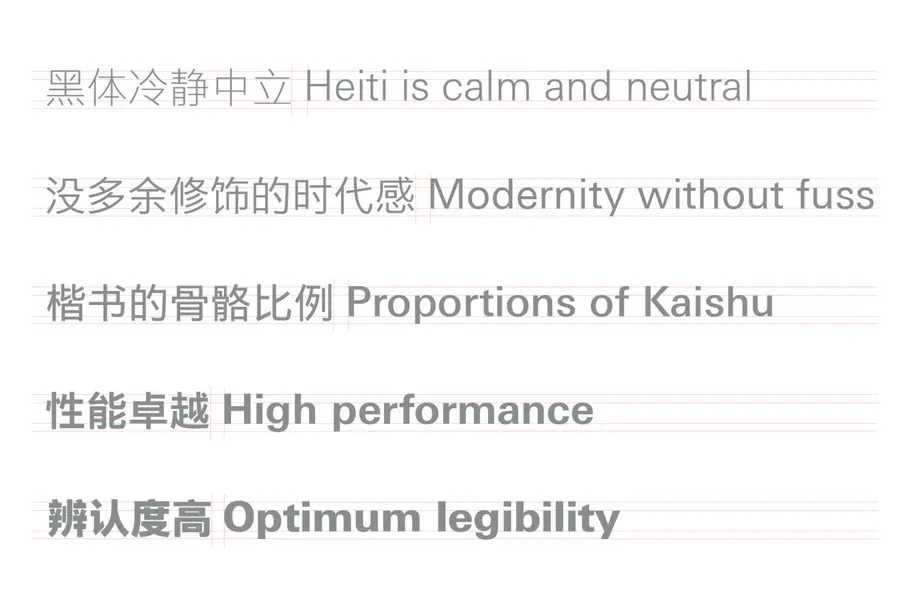
デジタル向けの中国語書体にサンセリフ体が誕生
M Ying Hei™は、Monotypeの熟練した書体デザイナーと長年コラボレーションを行ってきたKenneth Kwok、Robin Huiによってデザイン、制作されました。デジタルデバイスのインターフェイスと印刷媒体の両方で優れたパフォーマンスを発揮し、よりモダンでエレガントな中国語サンセリフ体を求める声に応える書体の開発に成功したのです。
ベストセラーの中国語書体を21世紀向けに一新
まず、M Ying Hei書体の由来をご紹介します。M Ying Heiは、優雅で上品な書体M Heiに大きなインスピレーションを受けています。M Heiは、1990年代にMonotypeがリリースしたクラシックなデザインの書体で、発表されるや否や瞬く間に中国語サンセリフ体のベストセラーとなりました。M Heiは、中国語繁体字の正式書体「楷書体」の構造とプロポーションをベースとしながら、ミニマルで鋭いストロークのデザインを取り入れたことから、Heiti系書体に分類されています。Heiti系は、1500年もの間、中国語における漢字の形体を定義してきた精巧な楷書体から装飾的要素を取り除いた、非常にシンプルな字体です。
M Ying Hei サンプル
中国語書体のすべてのカテゴリにおいて、Heitiはグラフィックデザイナーの間で最も人気のある書体となり、現代中国のライフスタイルを表現する代表的な文字としての存在を確立しました。それは、西洋でグロテスク・サンセリフ書体(Helvetica®など)が現代的な字体として定着したのと同じ現象と言えるでしょう。Heitiは、装飾要素を廃した落ち着いたトーンの書体で、読み手にモダンな雰囲気を印象づけます。言語の境界を越えて使用が可能で、縦横の線の太さが同じ書体ときれいに調和します。
Kaishuと同様の質を備えていることから、M Heiは他のHeitiデザインとは対照的に、比較的クラシックな構造をしています。
古いKaishu書体と新しいHeiti書体の両方の良い部分を併せもつM Heiは、中国語書体の世界における「稀に見る宝石」との呼び名が付くほどのデザインとなりました。また、香港と台湾では過去25年間にわたり、継続して読み続ける長文書用の書体として最も好まれる書体となりました。そして、モバイル技術の時代が到来したのです。
情報時代のための中国語サンセリフ体
携帯電話などの小型画面用に、滑らかで、可読性と柔軟性の高い中国語の書体に対する需要が高まることを予見したMonotypeの書体デザインチームは、デジタル画面でも美しく表示される高性能のHeiti書体の開発に乗り出しました。MonotypeのM Ying Hei書体は、この新しい時代の到来を念頭に制作されました。
M Ying Heiでは、漢字の中央部を広く取ることができます
かつては不可能だったことが、この新しいデザインで可能になったのはなぜでしょうか。M Ying Heiは、漢字の中央部を広く取ることができるのです。これは、ラテン文字でエックスハイトを大きくするのと似ています。この調整が可能になったことで、Neue Helveticaのようにはっきりとした機能的な書体との組み合わせが非常に美しく仕上がり、モダンで親しみやすい雰囲気を生み出すことができるようになりました。
また、最も重要な点は、漢字の中央部が広がることにより、デジタルデバイスのインターフェイスと紙媒体の両方で可読性が高まったことです。各文字内のスペースが広くなることで、標識や看板でも見やすくなり、バックライトのある画面も容易に克服できるようになったのです。
一目で読める高度な可読性
M Ying Hei書体は、可読性を最も重要視してデザインされており、車のダッシュボードやGPSシステムの情報表示の最適化を念頭に開発作業が展開されました。運転中は、道路から目を離す時間を最小限にとどめつつ、画面に表示された文字を素早く正確に読み取ることが必要です。そのため、この開発作業には通常よりも多大な配慮が要求されました。
使命は達成されたのです!「The effects of Chinese typeface design, stroke weight, and contrast polarity on glance based legibility」(『Display』刊行、MonotypeとMIT Age Labの研究員が共同執筆)によると、別のHei系、Ming系の書体に比べ、M Ying Heiは瞬読性が高いことがわかりました。たとえば、Monotype製のM Ying Hei系書体の中では可読性が最も低いMonotype Sung PRCでも、「Ming」系書体より認識時間が33.0%短縮、Microsoft YaHei Regularとの比較では20.9%、「Rounded Gothic(丸ゴシック)」書体のCYuen2PRC SemiBoldより19.0%短縮されています。
書体の可読性の高さは、正確な判読に必要な時間の長さと反比例するのです
他の書体と合わせることにも。
M Ying Heiには他にも優れた長所があります。グローバルブランドにとっては、Neue Helvetica®、Neue Frutiger®、Avenir® Next、Univers® Next、Trade Gothic® Next、Neue Haas Unica™などのコーポレート書体として人気の高いものとM Ying Heiが美しく組み合わせられることも、メリットの1つでしょう。
ほど良く配慮されたウエイトのバラエティ
あらゆるコンテンポラリーな字体で不可欠となった5種類のウェイトを揃えたM Ying Heiファミリーは、さまざまなアプリケーションの要求に対応可能、効果的な情報階層を構築します。ウェイトの遷移はスムーズ。印刷物からバックライト式標識、オフセット印刷、高解像・小画面のデバイスに至るまで、幅広いメディアに最適な表示を実現します。ウェイトのバリエーションにより、各種ラテン書体との併用も簡単です。
長く愛される次世代フォント
M Ying Heiファミリーは、Heiti書体と中国語書体全般に関してこれまで市場に存在していた大きな空白を埋めたと言えるでしょう。「生みの親」ともいえる元の書体から受け継いだ要素を踏まえると、M Ying Heiは現在世界中で活躍するデザイナーの力強い武器となり、今後も長く愛用されることでしょう。
Robin Hui
Robin Huiは1988年に書体デザイナーとしてMonotype Hong Kongに入社しました。現在 Monotype Hong Kongの主任デザイン・プロダクションマネージャーを務め、様々な書体デザインやテクノロジープロジェクトを任されています。異なるプラットフォーム間での書体の圧縮、ヒンティング、レンダリング制御も彼の仕事です。Monotypeへの入社前は、10年間プロの植字工を務め、書体の効果的な活用における経験を積み、中国語書体に対する強い情熱を抱くようになりました。